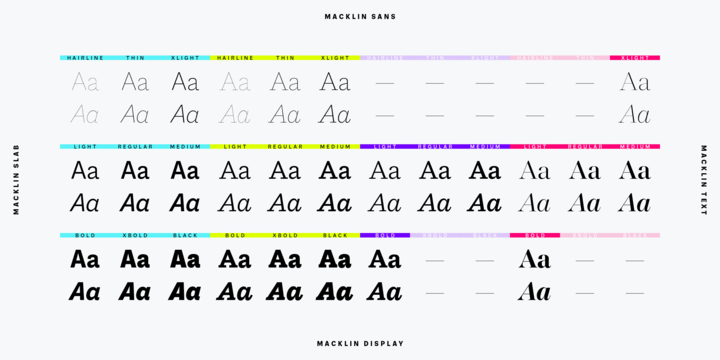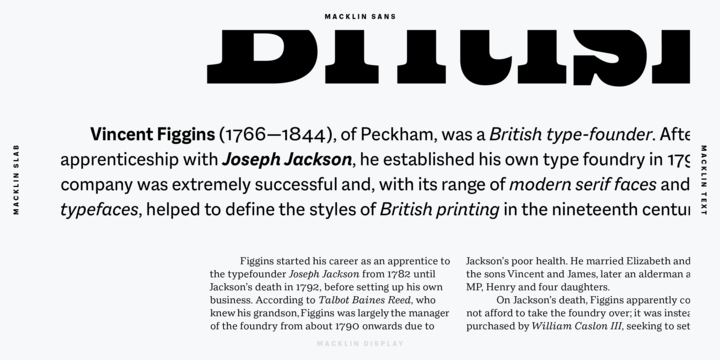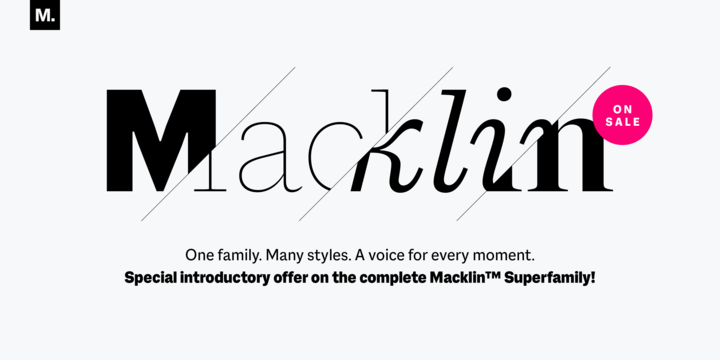
Aber auch hier:
Das R, ẞ, Fremdsprachen-g und fehlende Füßchen bei der Tabellen-1 in der Sans …
… muss man natürlich mögen.
Hmmm, ich habe sie mir gerade angeschaut und finde sie richtig ansprechend! Ich mag die Formen und die enorme Vielseitigkeit. In meinen Augen überwiegen die positiven Aspekte die kleinen Wermutstropfen deutlich. Die Lizenz könnte ich mir eigentlich mal zulegen. Danke für den Tipp R::bert! :huhu:
Dann noch mal zur Macklin:
Theoretisch ersetzen die 4 VF-Dateien ja die gesamten 54 statischen Schnitte. Praktisch wissen wir, dass es mit der VF-Unterstützung noch allerorts hapert. Aber um die Schrift mal auszutesten oder einfach in petto zu haben, ohne 50 Euro auszugeben, ist das Gratisangebot perfekt.
Sind „Variable Fonts“ so etwas wie „Multiple-Master-Schriften“, die es in den Neunziger Jahren mal gab und die sich damals™ nicht so richtig durchgesetzt haben?
Ja, das ist schon vergleichbar. Variable Fonts bieten aber noch mehr Freiheit bei der Definition der Achsen, zum Beispiel in Form einer Zeitachse.
Damals stellte man die gewünschten Parameter für die Multiple-Master-Fonts im Adobe Type Manager (ATM) ein. Ich wüsste nicht, dass es eine andere Möglichkeit gab. Erst dann konnte man mit den so erstellten Schnitten arbeiten. Die heutigen Variable Fonts können direkt zum Beispiel in InDesign manipuliert werden. Man sieht also sofort im Dokument, was sich am Schriftbild ändert. Das ist wesentlich komfortabler. Ich denke, daher hat das neue Format wirklich eine Chance, was ja bei den alten MM-Fonts nie der Fall war. Die haben sich einfach nicht durchgesetzt. Wollen wir hoffen, dass es diesmal besser läuft. (Dabei hatten wahrscheinlich die Leute die damals ATM hatten, mehr Ahnung von Schrift, als die heutigen 0815-Anwender, die ja schon die meisten OTF-Zückerchen nicht finden/anwenden können. :-?)
Sind „Variable Fonts“ so etwas wie „Multiple-Master-Schriften“, die es in den Neunziger Jahren mal gab und die sich damals™ nicht so richtig durchgesetzt haben?
Hier https://www.youtube.com/watch?v=NuCUUJ93qMQ&t=854s gibt es ab Minute 40 -- mit sehr viel Vortrag drumherum -- eine sehr anschauliche Erklärung der Möglichkeiten der Variable Fonts.
Edit: Pardon, eher Minute 41. :oops: